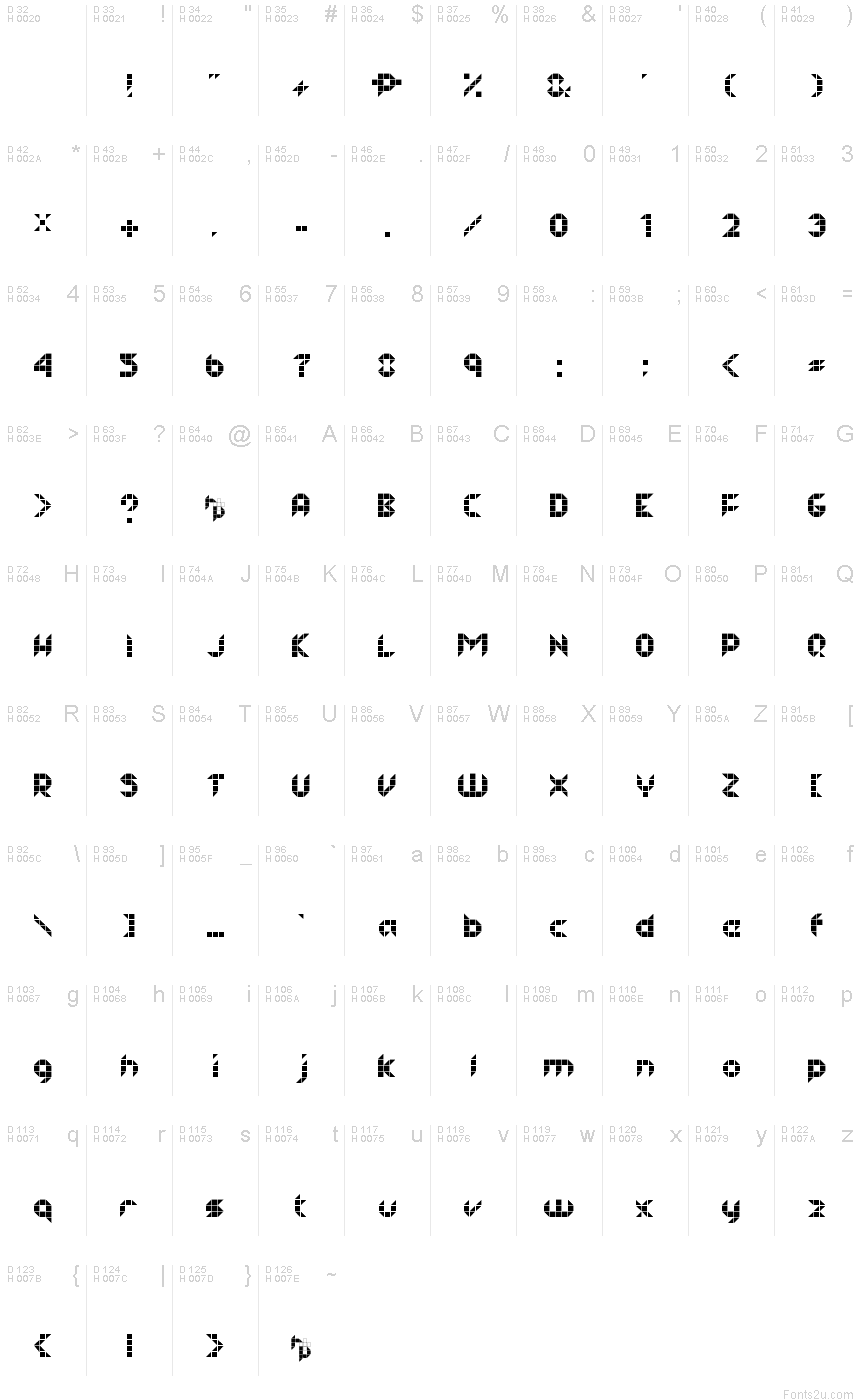
<p>Half Project Logo od Half Project to darmowy krój typu display w stylistyce techno, oparty na wyrazistej, modułowej siatce. Każda litera powstaje z połączenia masywnych kwadratów i ostrych trójkątów, tworząc pikselową teksturę, która jest jednocześnie retro i eksperymentalna. Surowe, czarno-białe formy przypominają cyfrowy szablon, nadając każdemu słowu techniczny, zaprojektowany charakter.</p>
<p>Dzięki Half Project Logo Twój tekst układa się w rytmiczne bloki, które świetnie wyglądają w logo, identyfikacji wizualnej wydarzeń, plakatach, tytułach gier czy eksperymentalnych okładkach albumów. Ten darmowy font najlepiej sprawdza się w dużych rozmiarach, gdzie w pełni ujawnia swój geometryczny wzór; idealnie łączy się z prostym, geometrycznym bezszeryfowym krojem w tekstach uzupełniających.</p>